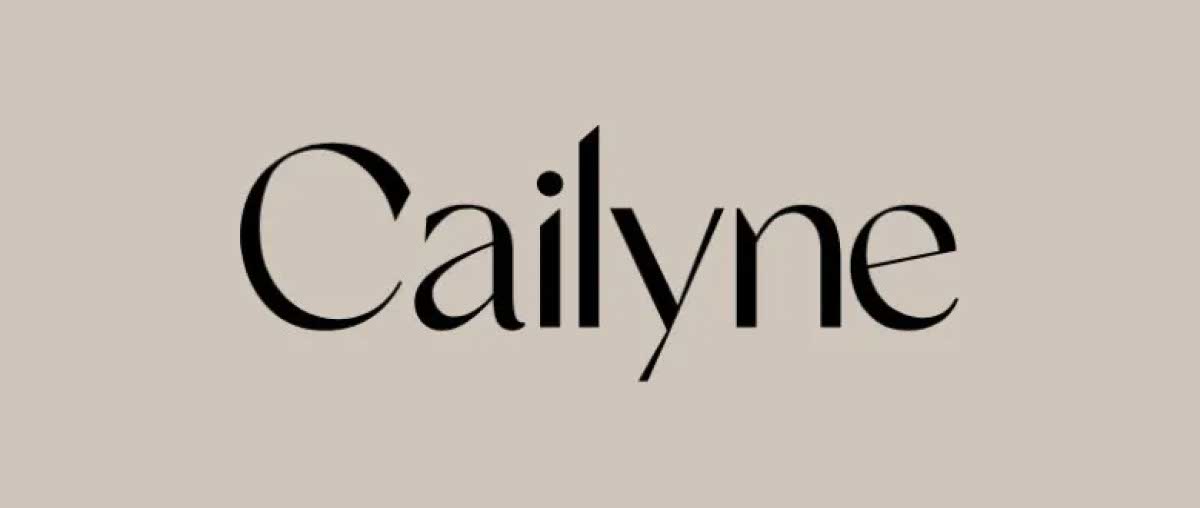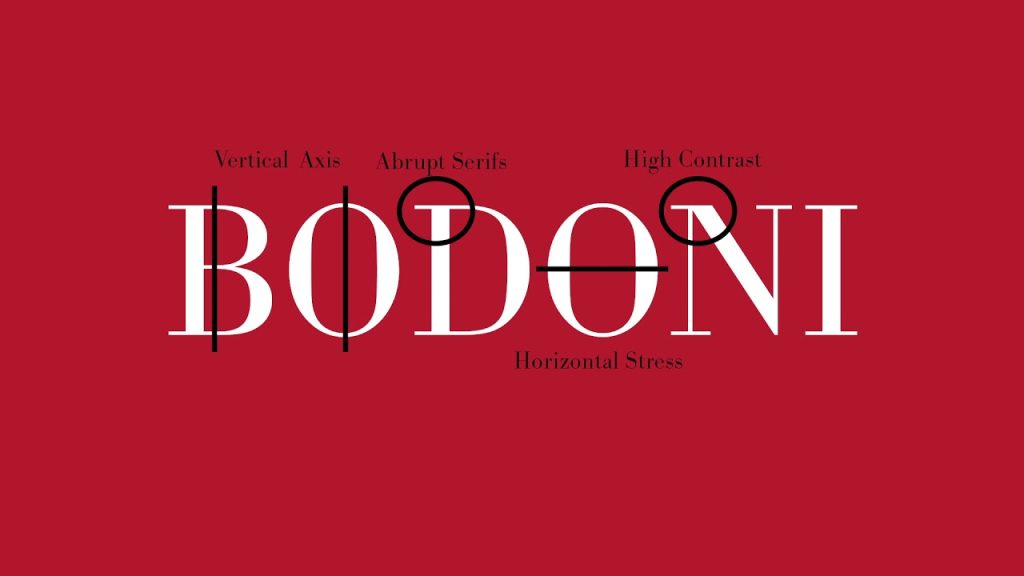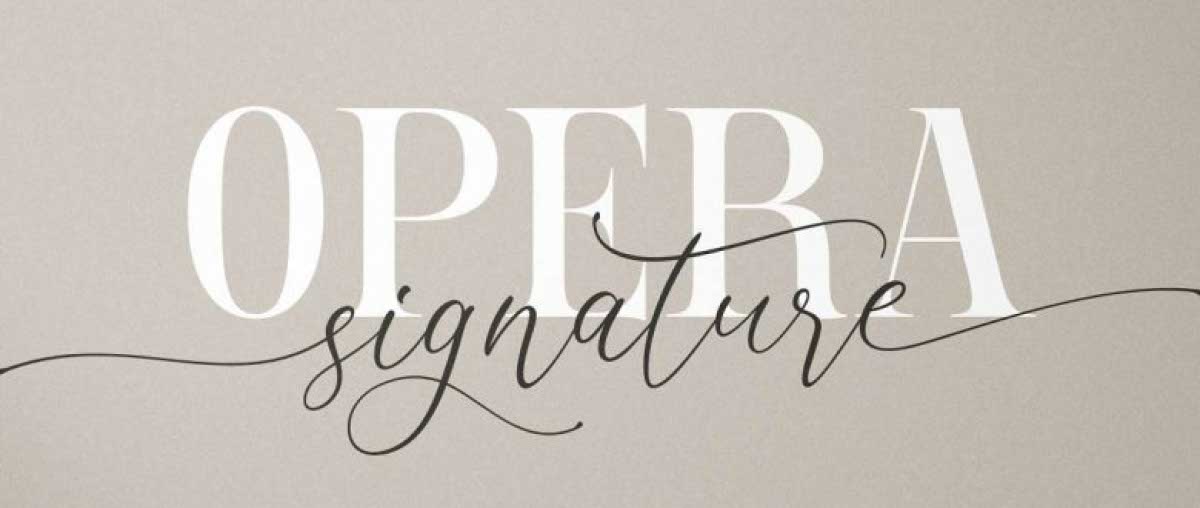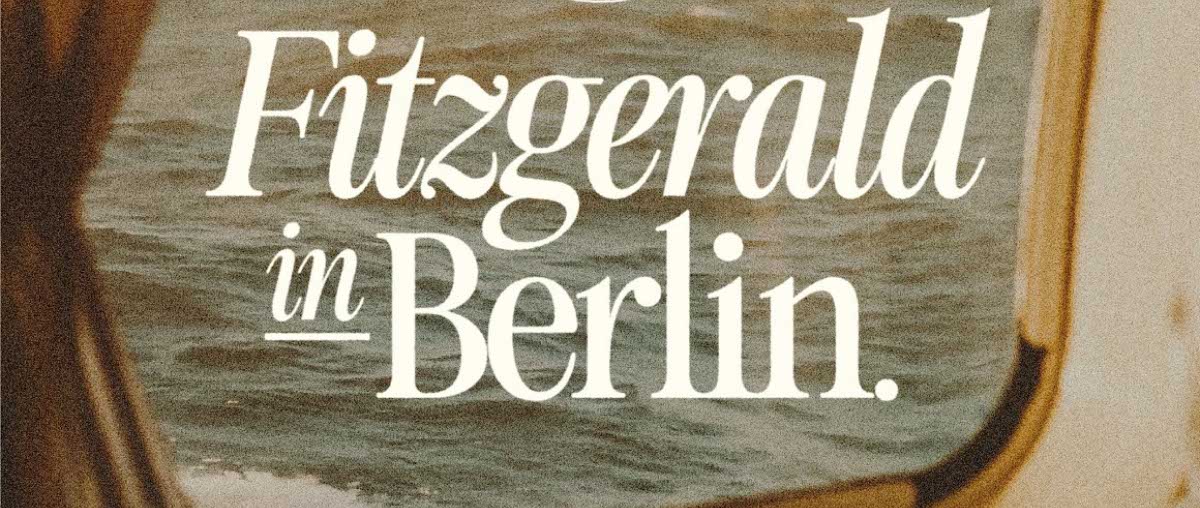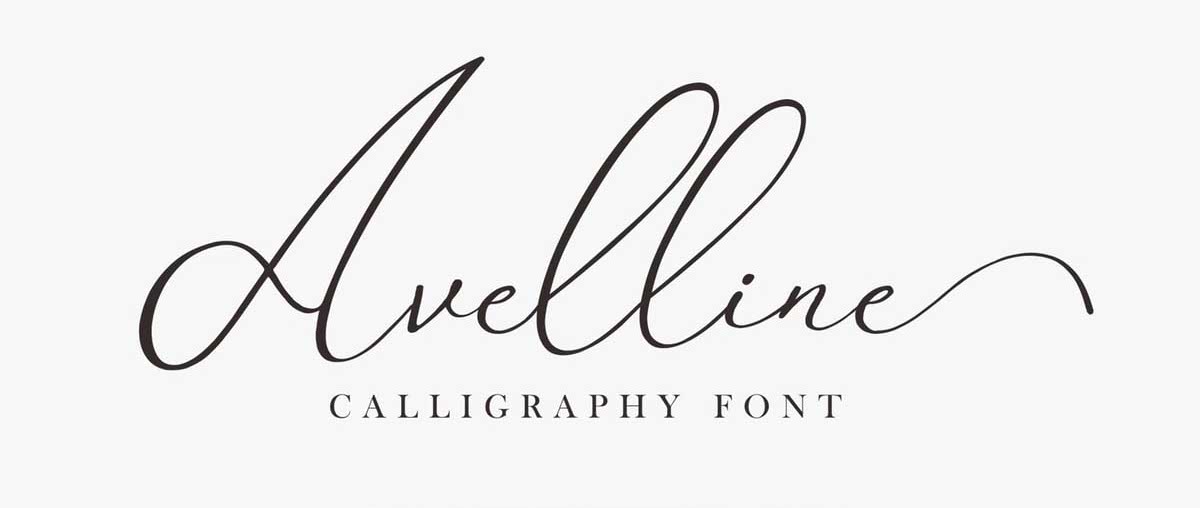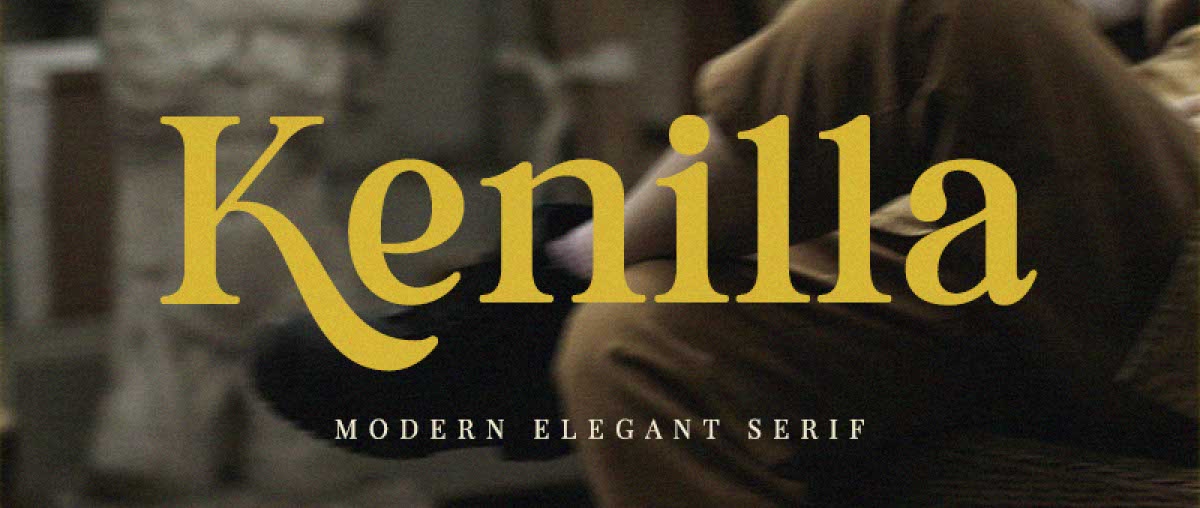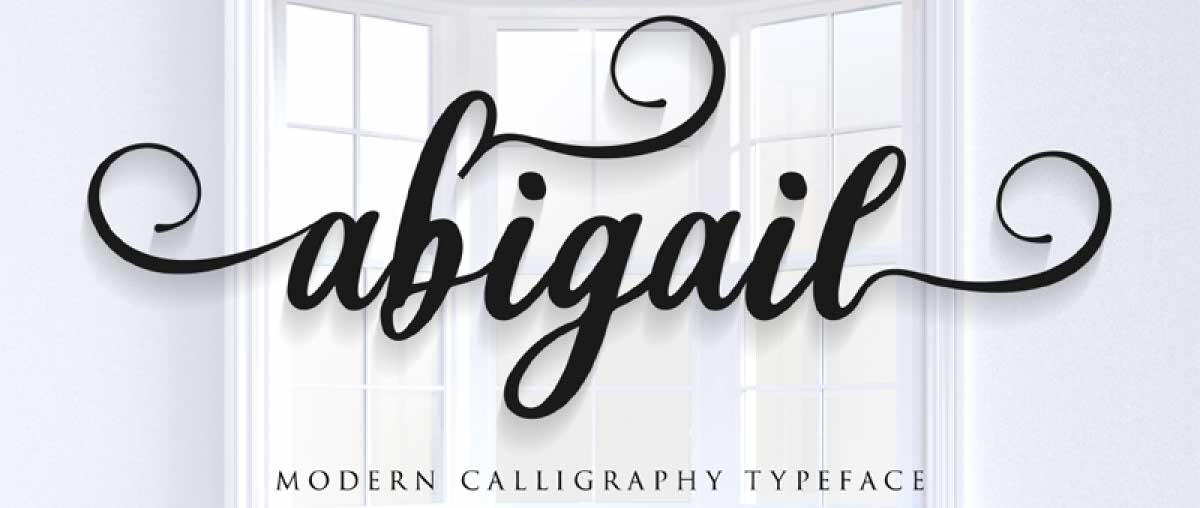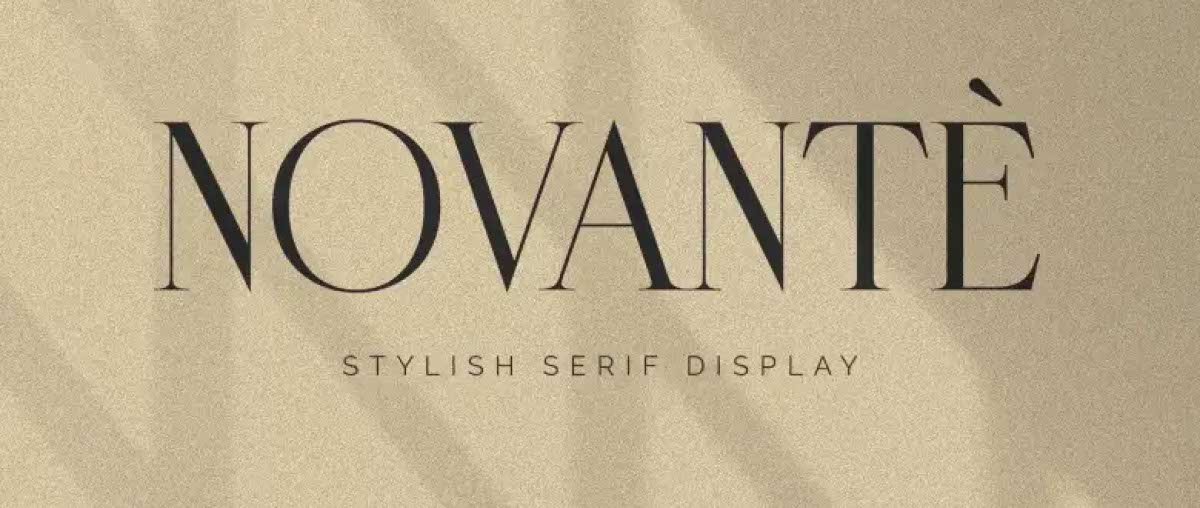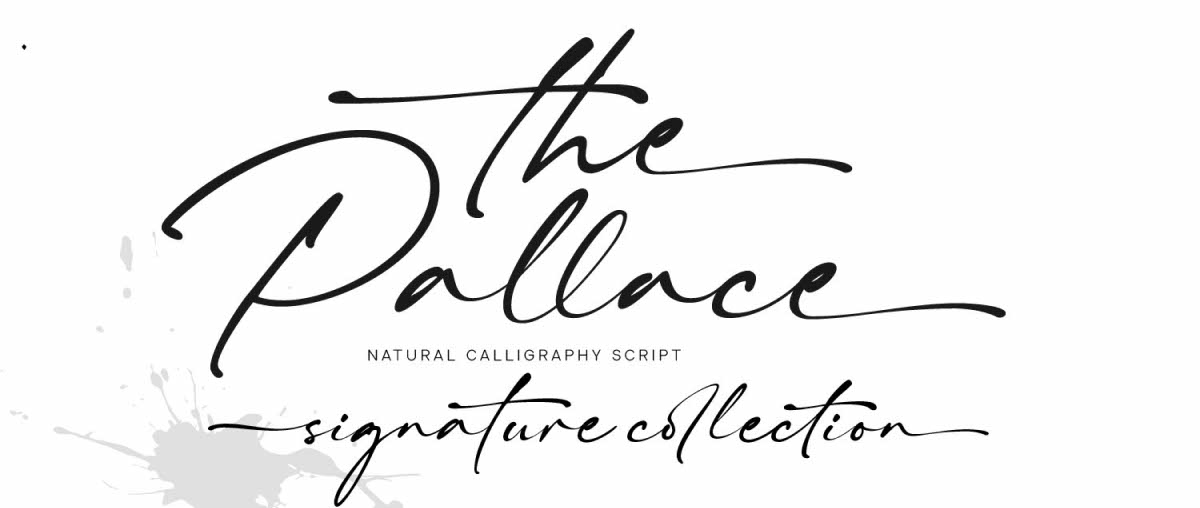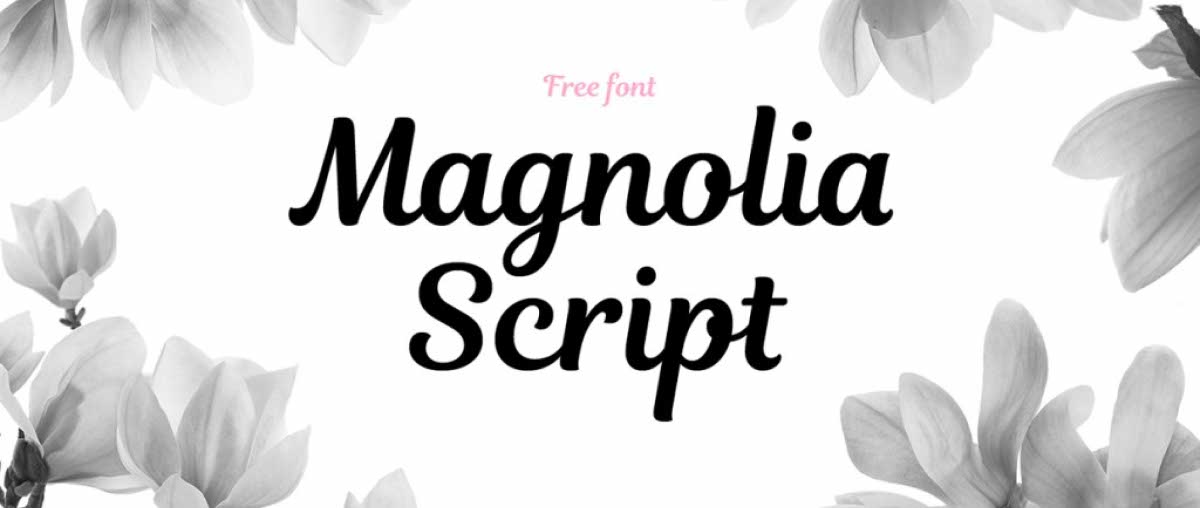
I. Font chữ sang trọng là gì?
Font chữ sang trọng là những font chữ mang đến cảm giác thanh lịch, tinh tế và cao cấp cho thiết kế. Chúng thường có những đặc điểm sau:
• Đường nét mảnh mai, sắc nét: Font chữ sang trọng thường có các đường nét mảnh mai, sắc nét, tạo cảm giác thanh lịch và tinh tế.
• Serif tinh tế: Serif là những nét móc nhỏ ở cuối các nét chữ. Font chữ sang trọng thường có serif tinh tế, góp phần tạo nên vẻ đẹp cổ điển và sang trọng.
• Khoảng cách chữ rộng rãi: Font chữ sang trọng thường có khoảng cách chữ rộng rãi, giúp cho bố cục văn bản trở nên thoáng mắt và dễ đọc hơn.
• Sự cân bằng và hài hòa: Font chữ sang trọng có sự cân bằng và hài hòa giữa các nét chữ, tạo cảm giác tổng thể đẹp mắt và tinh tế.
Ngoài ra, font chữ sang trọng còn có thể được tô điểm thêm bằng các chi tiết trang trí như hoa văn, họa tiết,… để tăng thêm vẻ đẹp và sự sang trọng cho thiết kế.
II. Tổng hợp 20+ font chữ sang trọng trong thiết kế
Việc lựa chọn kiểu chữ phù hợp trong thiết kế đồ họa có thể là yếu tố quyết định thành công của một dự án thiết kế. Một font tinh tế và sang trọng thể hiện đẳng cấp của thương hiệu và tôn lên vẻ đẹp của thiết kế. Mặc dù có nhiều loại font trên thị trường, nhưng không phải tất cả đều mang lại cảm giác sang trọng và tinh tế mà bạn mong muốn.
Terus sẽ xem xét hơn 20 font chữ sang trọng được ưa chuộng bởi nhiều nhà thiết kế trong phần này, những font mà bạn có thể tham khảo để sử dụng.
1. Prestigious
2. Karatone
3. Bodoni
4. Novante
5. Kenilla
6. Fitzgerald
7. Avelline
8. New York
9. Cotta
10. Vidaloka
11. Coldiac
12. Miyake Signature
13. Konseric
14. The Pallace
15. Abigail
16. Opera Signature
17. Cailyne
18. Glitten
19. Dream Avenue
20. Magnolia Script
21. Maglite
1. Prestigious
Prestigious
Prestigious là một font chữ sang trọng và thanh lịch, mang nét đẹp vừa hiện đại vừa cổ điển. Font serif này có thể được sử dụng để thiết kế thiệp cưới, bìa tạp chí, hình ảnh trên mạng xã hội hoặc bộ nhận diện thương hiệu. Prestigious sẽ nâng tầm mọi thiết kế của bạn với nét đẹp vượt thời gian của mình.
2. Karatone
Karatone
Letterhead Studio đã tạo ra Karatone, một font chữ serif hấp dẫn. Nhờ những nét cong mềm mại và gọn gàng của nó, font chữ này có thể được sử dụng cho nhiều phong cách thiết kế. Font Karatone rất phù hợp để thiết kế logo, bìa sách, nhãn sản phẩm và bao bì cho các công ty thời trang và mỹ phẩm.
3. Bodoni
Bodoni
Giambattista Bodoni đã tạo ra font chữ serif Bodoni vào thế kỷ 18. Bodoni có phong cách hiện đại, cổ điển và trang trọng, và nó nổi tiếng với độ tương phản tuyệt vời giữa các nét thanh và nét đậm. Trong các văn bản học thuật như nghiên cứu hoặc sách xuất bản, font chữ sang trọng này thường được sử dụng làm tiêu đề trên.
4. Novante
Novante
Novante Elegant Display Serif là một font chữ sang trọng và hấp dẫn. Cảm hứng của font chữ in hoa này là từ phong cách Art Deco kết hợp với phong cách tối giản hiện đại. Font chữ sang trọng này thường được sử dụng trong thiết kế chữ trên logo hoặc tiêu đề trong tạp chí có thể được thiết kế bằng font chữ này.
5. Kenilla
Kenilla
Kenilla là một font chữ serif hiện đại có nét đuôi mượt mà và độc đáo. Kenilla, được thiết kế bởi BrandSemut, nhanh chóng được yêu thích nhờ các nét gọn gàng và các đường cong linh hoạt. Font chữ sang trọng này thường được sử dụng trong thiết kế logo, tiêu đề tạp chí, bao bì trang sức hoặc thiệp mời có thể được tạo bằng font chữ này.
6. Fitzgerald
Fitzgerald
Fitzgerald, có vẻ đẹp thanh lịch nhưng hơi hoài cổ, là một sự lựa chọn tuyệt vời cho các thiết kế theo phong cách vintage. Fitzgerald không chỉ đẹp và hấp dẫn mà còn dễ đọc và phù hợp để làm nội dung chính hoặc tiêu đề của thiết kế. Có thể sử dụng font chữ sang trọng này trong thiết kế bao bì và các ấn phẩm xuất bản, chẳng hạn như bìa tạp chí.
7. Avelline
Avelline
Avelline là một font chữ script đẹp mắt có thể mang lại cảm giác nhẹ nhàng và tinh tế cho thiết kế của bạn. Avelline, mang đậm phong cách lãng mạn, là sự lựa chọn tuyệt vời cho các thiết kế thiệp cưới, thư mời, logo thương hiệu và ấn phẩm cho phái nữ cần mềm mại và sang trọng.
8. New York
New York
Nhờ độ tương phản cao giữa nét thanh và nét đậm, New York là một font chữ có chân sang trọng có nét đẹp thanh lịch. New York là nơi phù hợp nếu bạn cần một font chữ sang trọng nhưng không quá cầu kỳ. Font chữ sang trọng này thường được sử dụng trong thiết kế bưu thiếp, poster, bìa tạp chí thời trang, poster hoặc chữ trang trí trong nhiếp ảnh là những ví dụ về font chữ này.
9. Cotta
Cotta
Megi Satyo Widodo đã thiết kế Cotta, một font chữ có chân sang trọng mang đậm phong cách nữ tính. Thiết kế logo, thiệp mời, tạp chí và bộ nhận diện thương hiệu có thể sử dụng font chữ này. Ngoài ra, loại font chữ sang trọng này dễ sử dụng trên nhiều loại thiết kế hiện đại và hỗ trợ nhiều ngôn ngữ.
10. Vidaloka
Vidaloka
Vidaloka, một font serif được tạo ra vào năm 2011 bởi các nhà thiết kế đồ họa Alexei Vanyashin và Olga Karpushina, là lý tưởng cho các tiêu đề và đoạn văn bản cần nhấn mạnh. Vidaloka, với đặc điểm dễ đọc ở kích thước lớn, có thể làm nổi bật nội dung nhờ độ tương phản nét thanh và nét đậm cao.
11. Coldiac
Coldiac
Coldiac là một họ font serif hiện đại dựa trên phong cách serif chuyển tiếp. Coldiac mang đến cảm giác thanh lịch và tinh tế nhờ sự tương phản nhẹ giữa các nét thanh và đậm. Font chữ sang trọng này thường được sử dụng trong thiết kế logo, thư chào mừng, poster, danh thiếp, slider trên blog và đồ văn phòng phẩm đều có thể sử dụng font chữ này.
12. Miyake Signature
Miyake Signature
Một trong những font chữ viết tay thanh lịch nhất là Miyake Signature. Font chữ này có thể mang lại cho thiết kế của bạn sức hút tinh tế và nữ tính. Nét chữ mềm mại và ấn tượng của font chữ sang trọng này khiến nó trở thành một lựa chọn tuyệt vời cho các phần chữ ký trong thiệp mời, bao bì sản phẩm hoặc các thiết kế quảng cáo thương hiệu cá nhân.
13. Konseric
Konseric
Font serif Konseric nổi bật với những đường cong và vết cắt đặc biệt làm cho nó khác biệt so với các font khác. Các ký tự in hoa của font chữ này có các nét nối và cách điệu đặc biệt. Các dự án thiết kế yêu cầu cả nét đẹp cổ điển và nét sang trọng, hiện đại có thể sử dụng font Konseric, hỗ trợ nhiều ngôn ngữ.
14. The Pallace
The Pallace
Muhammad Ridha Agusni và Siti Saribanon Nurjannah đã thiết kế The Pallace, một font chữ sang trọng và thanh lịch. Font chữ sang trọng này, được thiết kế dựa trên chữ viết tay đầy cuốn hút, có các nét uyển chuyển và đẹp mắt. Nó phù hợp với các thiệp mời, bìa sổ tay và bài đăng mạng xã hội.
15. Abigail
Abigail
Các nét chữ của Abigail có độ mảnh vừa phải và các góc bo tròn mềm mại, tạo nên một font chữ tao nhã và nhẹ nhàng. Do dễ đọc, font chữ sang trọng này thường được sử dụng trong thiết kế logo, bìa tạp chí, tiêu đề tạp chí hoặc chữ trên hình ảnh quảng cáo.
16. Opera Signature
Opera Signature
Có hai loại font chữ: serif và script trong bộ font chữ Opera Signature Duo. Cả hai bộ chữ đều có thiết kế thanh lịch và sang trọng. Các đường nét mảnh mai, sắc nét với các chi tiết serif tinh tế mang đến vẻ đẹp thanh lịch và cổ điển của Opera Serif. Opera Script, trong khi đó, có các nét uyển chuyển, mềm mại, lãng mạn và bay bổng.
17. Cailyne
Cailyne
Cailyne, một font chữ serif hiện đại, có hai dạng: chữ thường và chữ nghiêng. Font chữ sang trọng này thích hợp cho các thiết kế logo, biển hiệu, danh thiếp, phong bì hoặc thiệp chúc mừng vì diện mạo thanh lịch của nó.
18. Glitten
Glitten
Glitten là một font chữ serif tinh tế được thiết kế bởi BrandSemut. Hơn nữa, font chữ này cung cấp hơn 98 thiết kế cho chữ ghép để hỗ trợ thiết kế sáng tạo. Font chữ sang trọng này có thể được sử dụng để tạo logo, bìa tạp chí hoặc hình quảng cáo trên mạng xã hội vì nó dễ dùng và tinh tế.
19. Dream Avenue
Dream Avenue
Dream Avenue sử dụng font chữ serif hiện đại thanh lịch và tinh tế. Muntab Art là tác giả của font chữ sang trọng này. Dream Avenue, với phong cách hiện đại pha chút cổ điển, là một địa điểm tuyệt vời để thiết kế các bức tranh, hình minh họa, nhãn dán, logo và poster cho các thương hiệu thời trang và trang sức.
20. Magnolia Script
Magnolia Script
Magnolia Script là một font chữ serif gọn gàng, hiện đại. Một diện mạo tinh tế sẽ được mang đến cho thương hiệu và thiết kế của bạn với phong cách chữ viết tay Magnolia tinh tế và mềm mại. Font chữ sang trọng này có thể được sử dụng trong thiết kế thiệp cưới ngoài mục đích thương mại.
21. Maglite
Maglite
Maglite, một font chữ serif thanh lịch, là một lựa chọn tuyệt vời để thiết kế thiệp cho các sự kiện quan trọng, chẳng hạn như đám cưới. Maglite, do Sarid Ezra thiết kế, nổi bật với những nét chấm móc ấn tượng, mới lạ nhưng vẫn nhẹ nhàng và tinh tế.
Bài viết là các thông tin về các font chữ sang trọng, tinh tế dành cho dân designer mà Terus muốn gửi đến cho quý đơn vị đang hợp tác đến Terus và bạn bè doanh nghiệp của Terus.
Hi vọng bài viết có thể giúp ích được cho bạn, cảm ơn bạn đã đọc hết bài viết.
Nếu bạn có bất cứ yêu cầu gì về Terus có thể liên hệ tại đây nhé!
Theo dõi Terus tại:
FAQ – Giải đáp các thắc mắc về các font chữ sang trọng
1. Làm thế nào để kết hợp font chữ sang trọng với các font chữ khác?
Khi kết hợp font chữ sang trọng với các font chữ khác, Terus sẽ đưa ra cho bạn một số điều cần lưu ý sau:
• Chọn font chữ có phong cách tương đồng: Ví dụ, bạn có thể kết hợp font chữ serif sang trọng với font chữ sans-serif hiện đại hoặc font chữ script thanh lịch.
• Sử dụng tỷ lệ tương phản phù hợp: Nên sử dụng font chữ có kích thước khác nhau để tạo sự tương phản và thu hút sự chú ý. Tuy nhiên, cần đảm bảo rằng tỷ lệ kích thước giữa các font chữ là hợp lý, tránh gây khó chịu cho người đọc.
• Hạn chế sử dụng quá nhiều font chữ: Nên sử dụng tối đa 2-3 font chữ trong cùng một thiết kế để tránh gây rối mắt và mất tập trung.
• Đảm bảo tính dễ đọc: Font chữ cần phải dễ đọc và dễ hiểu, ngay cả khi được sử dụng ở kích thước nhỏ.
2. Nên sử dụng font chữ sang trọng cho những loại nội dung nào?
Font chữ sang trọng thường được sử dụng cho những loại nội dung sau:
• Logo và thương hiệu: Font chữ sang trọng có thể giúp tạo ấn tượng mạnh mẽ và chuyên nghiệp cho logo và thương hiệu của bạn.
• Thiết kế cao cấp: Font chữ sang trọng có thể được sử dụng trong các thiết kế cao cấp như thiệp cưới, bao bì sản phẩm, tạp chí,…
• Nội dung mang tính trang trọng: Font chữ sang trọng có thể được sử dụng cho các nội dung mang tính trang trọng như văn bản pháp lý, thông báo chính thức,…
3. Cần lưu ý gì khi sử dụng các font chữ sang trọng?
• Font chữ sang trọng có thể không phù hợp với tất cả các thiết kế. Hãy cân nhắc kỹ lưỡng trước khi sử dụng font chữ sang trọng cho thiết kế của bạn.
• Nên sử dụng font chữ bản quyền để tránh vi phạm luật bản quyền.
• Font chữ sang trọng thường có giá cao hơn các font chữ thông thường. Hãy cân nhắc ngân sách của bạn trước khi mua font chữ sang trọng.
4. Nên sử dụng font chữ serif hay sans-serif cho font chữ sang trọng?
Cả font chữ serif và sans-serif đều có thể được sử dụng cho font chữ sang trọng. Việc lựa chọn font chữ phù hợp phụ thuộc vào phong cách thiết kế và nội dung mà bạn muốn truyền tải.
• Serif: Thường được sử dụng cho các thiết kế mang tính truyền thống, trang trọng, hoặc muốn tạo cảm giác cao cấp.
• Sans-serif: Thường được sử dụng cho các thiết kế hiện đại, trẻ trung, hoặc muốn tạo cảm giác đơn giản, dễ đọc.
5. Một số mẹo để sử dụng font chữ sang trọng hiệu quả là gì?
• Sử dụng font chữ với độ phân giải cao: Font chữ có độ phân giải cao sẽ giúp hiển thị rõ ràng và sắc nét, tạo cảm giác sang trọng hơn.
• Chú ý đến khoảng cách giữa các chữ và dòng chữ: Khoảng cách phù hợp sẽ giúp bố cục văn bản trở nên thoáng mắt và dễ đọc hơn.
• Sử dụng màu sắc phù hợp: Màu sắc có thể ảnh hưởng đến cảm giác của font chữ. Hãy chọn màu sắc phù hợp với phong cách thiết kế và nội dung của bạn.
• Tránh sử dụng quá nhiều hiệu ứng: Việc sử dụng quá nhiều hiệu ứng có thể khiến font chữ trở nên rối mắt và mất đi vẻ đẹp sang trọng.